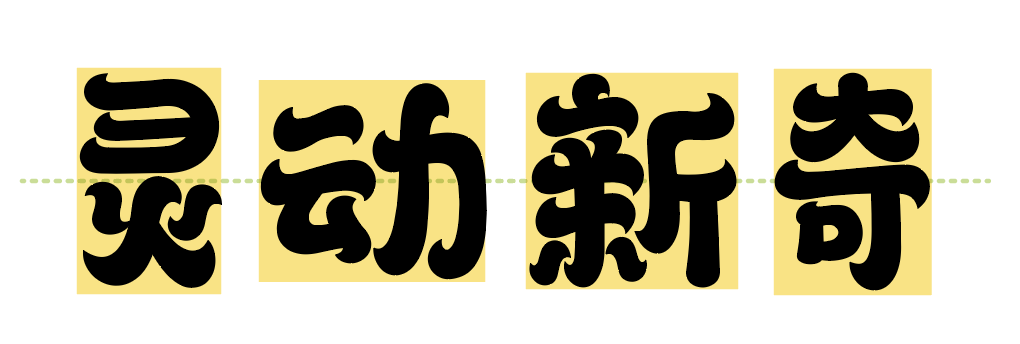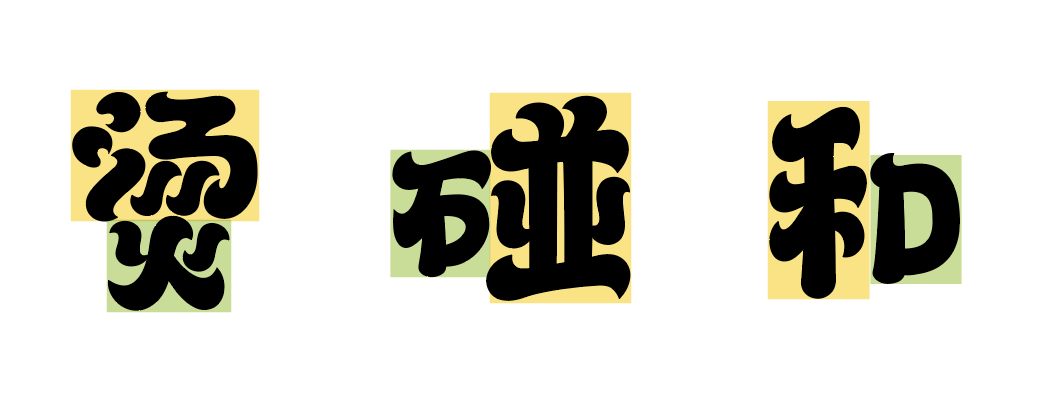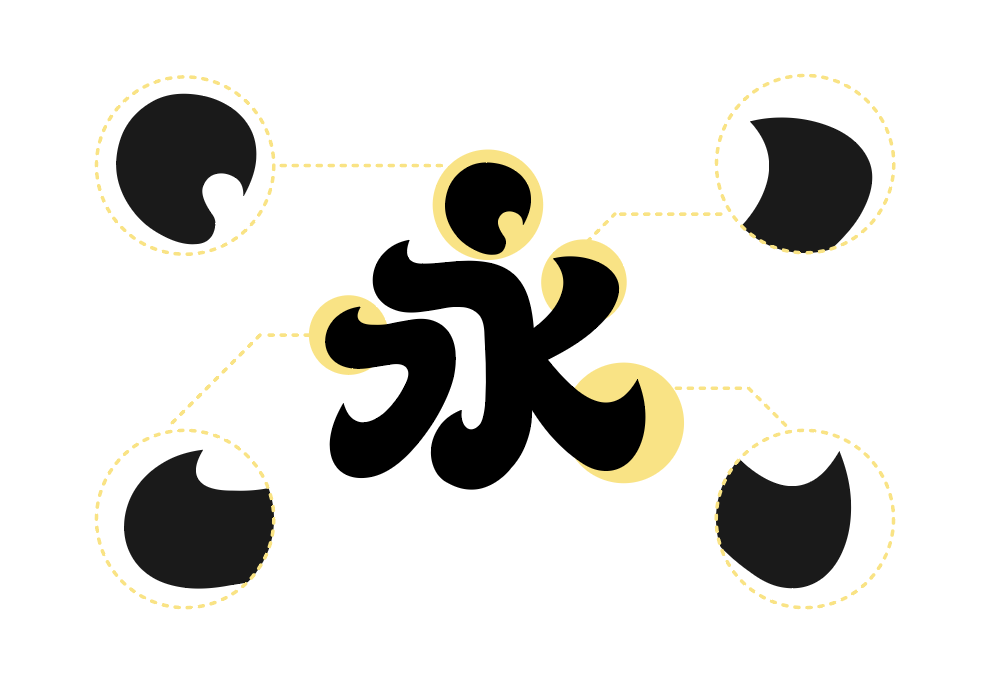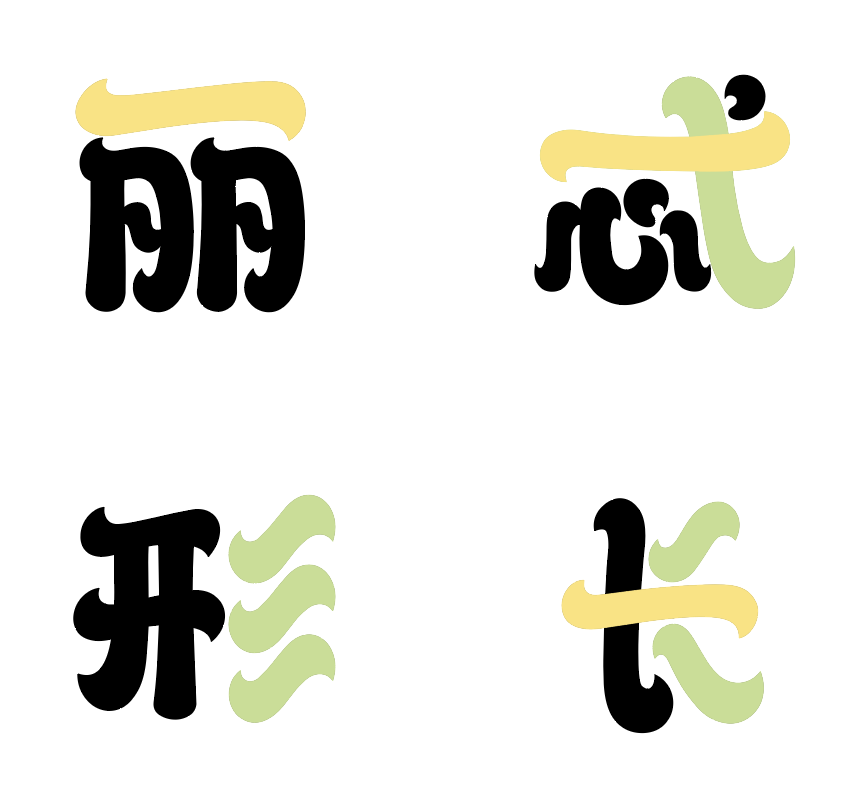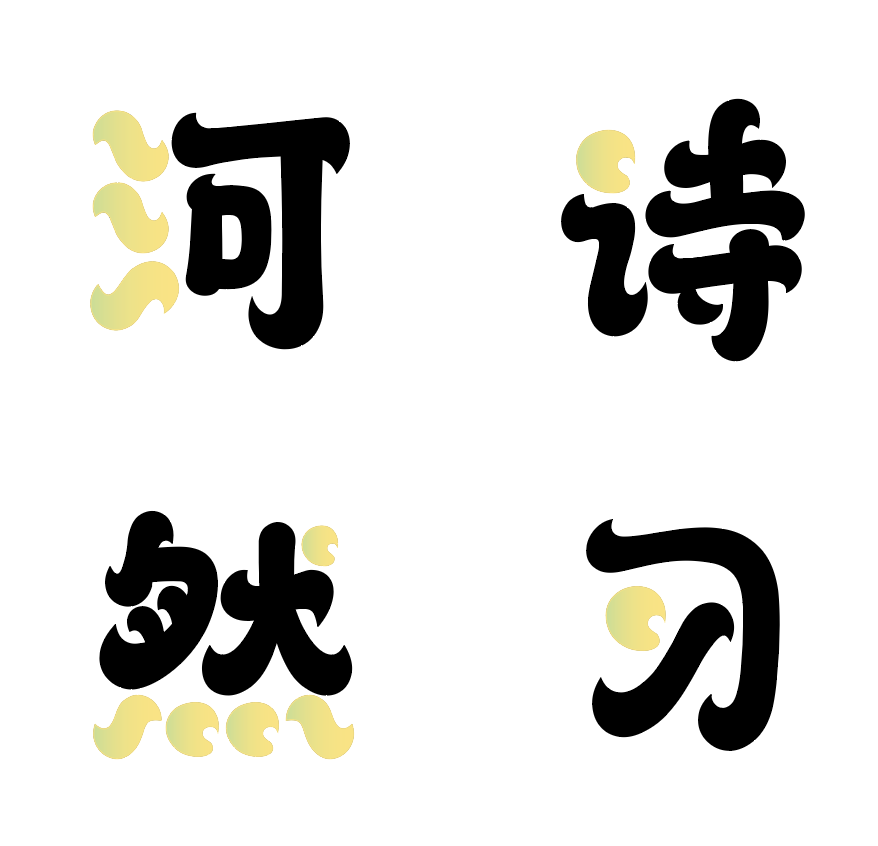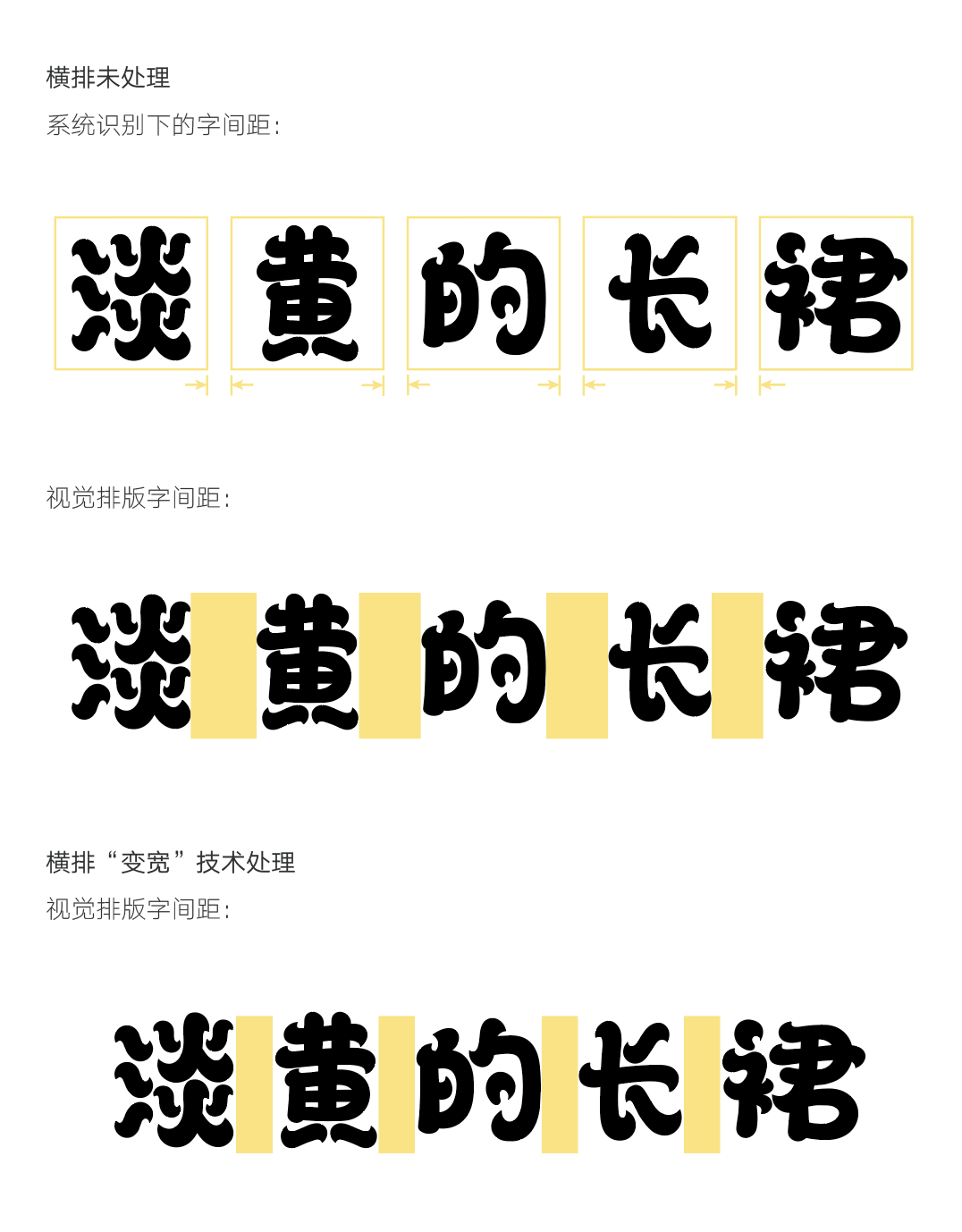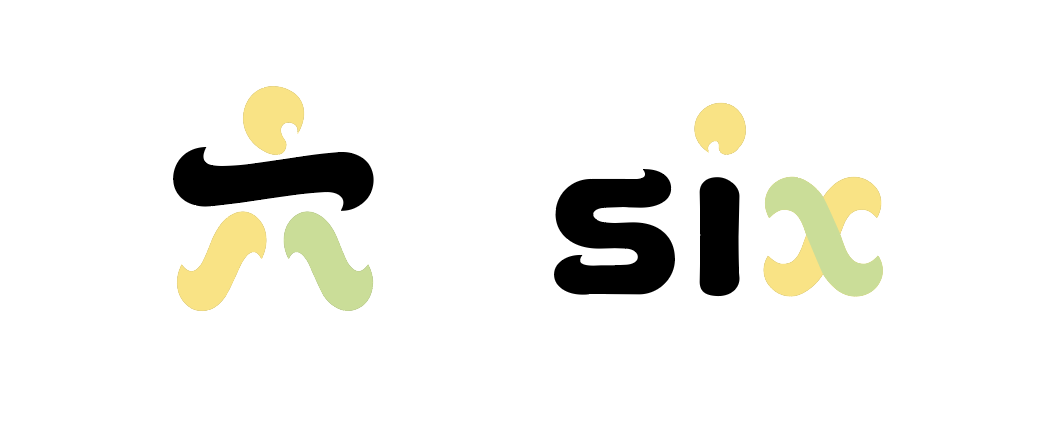
汉仪铸字旺财 | 整体特点
“汉仪铸字旺财”是汉仪旗下的“铸字社工作室”打造的一款创意美术标题字。设计师用“柔和流畅的曲线”和“灵活多变的字体结构”形象的刻画出了一只蹦蹦跳跳、顽皮可爱的小狗,十分惹人喜爱。
汉仪铸字旺财 | 字形多变
“汉仪铸字旺财”的字形变化多样,依据字体结构而呈现出或长或方或扁的节奏变化。好似顽皮的小狗一样蹦蹦跳跳、十分可爱。
汉仪铸字旺财 | 结构灵活
“汉仪铸字旺财”部分字体的偏旁与部首版率占比差距大,单字结构变化丰富,为字体增添了许多趣味性。
汉仪铸字旺财 | 笔画活泼
“汉仪铸字旺财”的笔画均采用弧线带勾的处理方式,好像兴奋的小狗在摇晃尾巴一样,丰富了字体的性格特点。
“汉仪铸字旺财”的横、撇和捺的起笔与收笔处均以小勾装饰,且两端勾的弯曲方向相反,形成了鲜明对比。
“汉仪铸字旺财”的点笔画十分饱满,它根据部首的不同而设定为月牙形和长钩形。笔画曲线柔和流畅,如行云流水一般。
汉仪铸字旺财 | 技术特点
由于“汉仪铸字旺财”不同字体字面差异较大,在考虑到排版使用上的体验感后,我们在技术上采用了字间距变宽的处理方式,使字体的排版效果更加舒适自然。
汉仪铸字旺财 | 中西文匹配
“汉仪铸字旺财”的西文字母充分吸收了中文笔画活泼、可爱的性格特点,中西文搭配使用十分和谐。